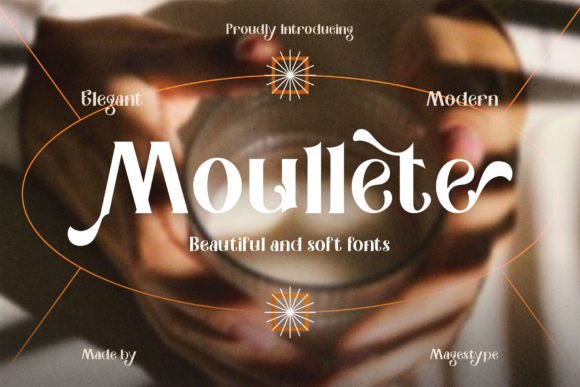
[Creativefabrica] Moullete Font (2021)
Moullete - это стильный, смелый и невероятно элегантный шрифт с засечками.
Он потрясающе смотрится на свадебных приглашениях, благодарственных открытках, цитатах, поздравительных открытках, логотипах, визитных карточках и любом другом дизайне, требующем индивидуального подхода.